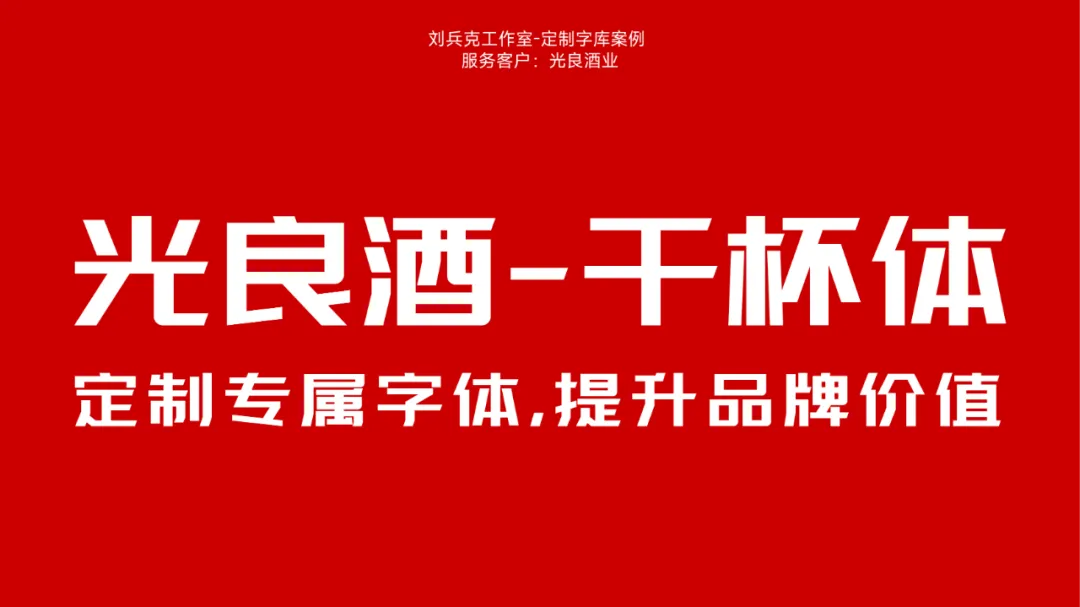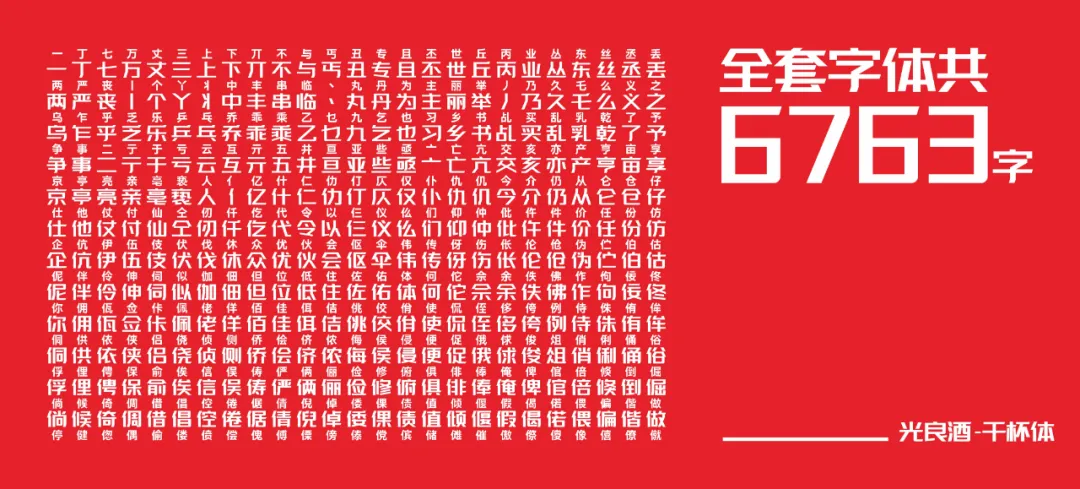
光良酒 – 干杯体是四川光良酒业推出的一款免费可商用品牌定制字体,由字体江湖团队历时 9 个月设计完成,于 2023 年 1 月 6 日正式上线,也是业内首个推出开源字体的白酒品牌。
光良酒干杯体执行 GB2312 标准,包含简体 6763 字+其他字母字符等,并包含55个不同的“酒”字标识,以及原料、香型、货运等数十个标识。是一款很好用、很实用的标题类字体,特别适合海报、包装、宣传物料等场景的标题设计。当然了,通用性也很强,不仅适配白酒行业,也适用于各行各业品牌的视觉传播。